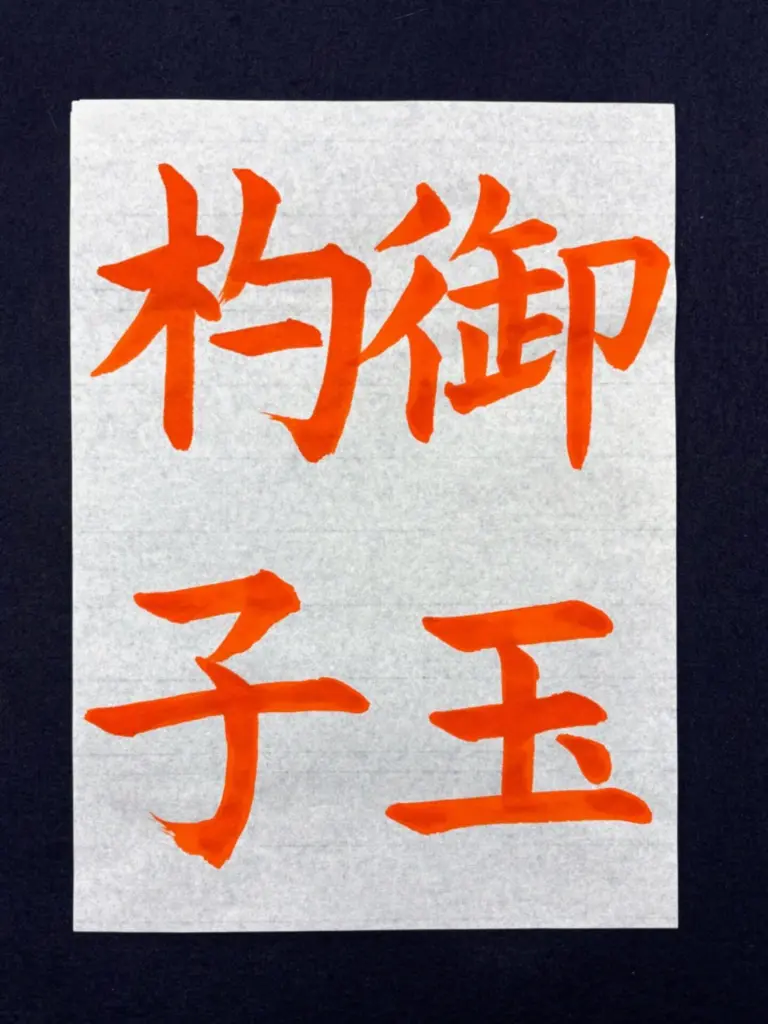
「おたまじゃくし」って、こんな漢字で書くんですね!読者の皆さんはご存知でしたか?
先日、4年生の男の子が「おたまじゃくしを漢字で書いてみたい!」と言ってくれました。かわいい響きの言葉なのに、難しそうな漢字になるのがかっこいい!というのが理由だったようです。
そのリクエストを受けて、私は「御玉杓子」というお手本を書きました。(勿論、漢字はしっかり調べました(笑))
すると、その後のクラスで別の生徒さんがそのお手本を見て「なんて読むの?」と興味津々!せっかくなので、私はクイズを出してみました。「この字、なんて読むと思う〜??」
ヒント① 生き物。ヒント② 「子」は「し」と読む。子どもたちが一生懸命に考えながら、いろんな答えを出してくれるのがとても面白かったです。
さて、今回はそんな「御玉杓子」について、意味や書き方のポイントをお伝えします!
2. 「御玉杓子」の意味と読み方
「御玉杓子」は「おたまじゃくし」と読みます。
「おたまじゃくし」は、カエルの子どもですね。では、どうしてこのような漢字になるのでしょうか?
- 「御玉」…「玉」は丸い形を表し、「御」がつくことで丁寧な表現になります。
- 「杓子」…「杓子(しゃくし)」は、おたまのような柄のついた器のこと。
つまり、「御玉杓子」は “まるくて、おたまのような形をしたもの” を指し、おたまじゃくしの姿からこの漢字が使われるようになったのです。
子どもたちにこの説明をすると、「なるほど!」「たしかに、形が似てる!」と納得していました。
「御」:左中右のバランスを意識
「御」は、左の「彳(ぎょうにんべん)」、中央と右の部分の「卸」のバランスが重要です。
- ぎょうにんべんは、1画目と2画目の方向の違いに気をつけましょう。
- 右側の「卸」の部分は、縦にすっきり並ぶよう意識するときれいに見えます。
「玉」:大きさや形を意識
- 「玉」は、シンプルな形なので、筆の入りと終わりを意識すると美しくなります。
- 「御」や「杓」と比べて画数が少ないので小さめに、縦に長い字になりすぎないようにしましょう。
「杓」:はねの動きをしっかり
- 木偏(きへん)と旁(つくり)のバランスを意識しましょう。
- 「杓」は、縦画の最後の「はね」がポイントです。
- しっかりとはねることで、字にメリハリが出ます。
「子」:脚を長く見せる
- 「子」は、横線から下の部分が長く見えると全体の印象が整います。
- 3画目の横線は、1・2画目の交わる部分のすぐ下に来るように書きましょう。
普段ひらがなで書いているものも、こうして毛筆で漢字を使って書いてみると、その形や成り立ちの面白さに気づきます。
今回の練習では、「御」のバランス、「玉」の大きさ、「杓」のはね、「子」の脚の長さ など、それぞれの字のポイントを意識しました。どれも書きごたえのある漢字ですね。
生徒たちも「なんて読むの?」と興味を持ちながら取り組んでくれました。こうした言葉との出会いが、書道の楽しさにつながると嬉しいです。